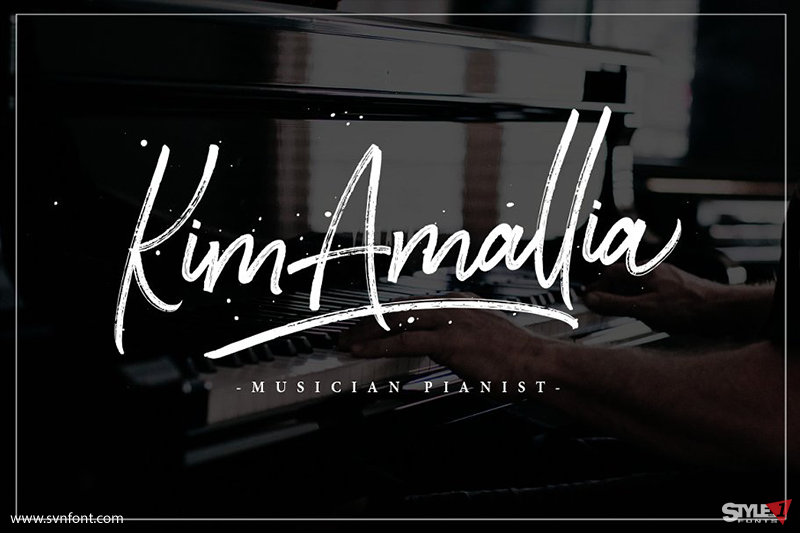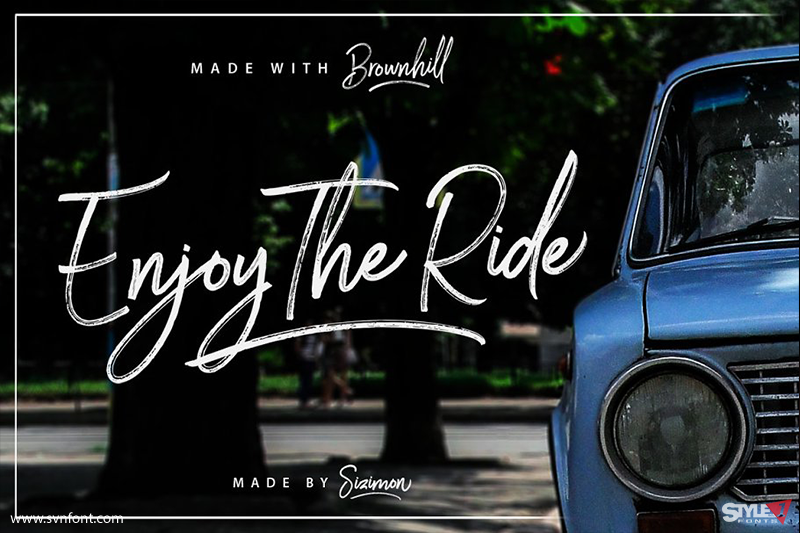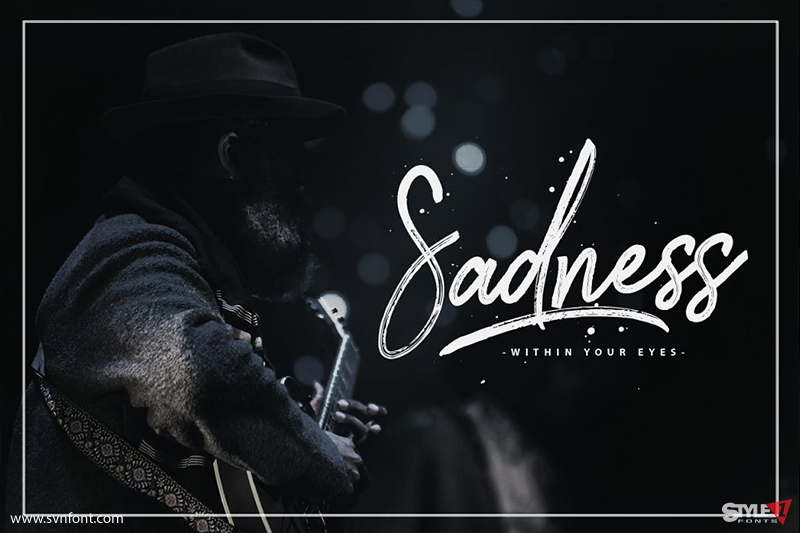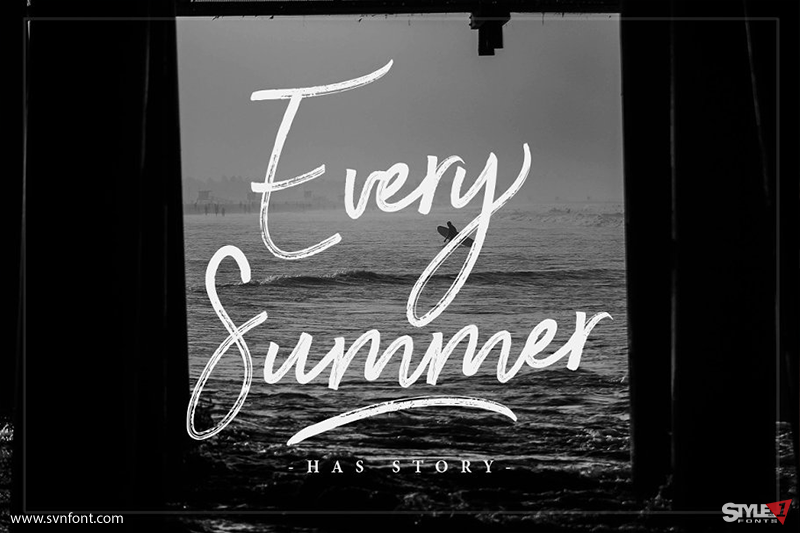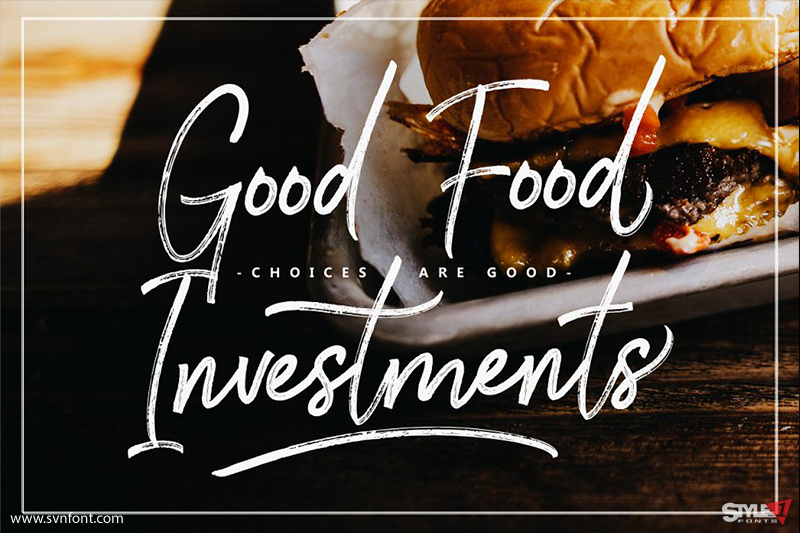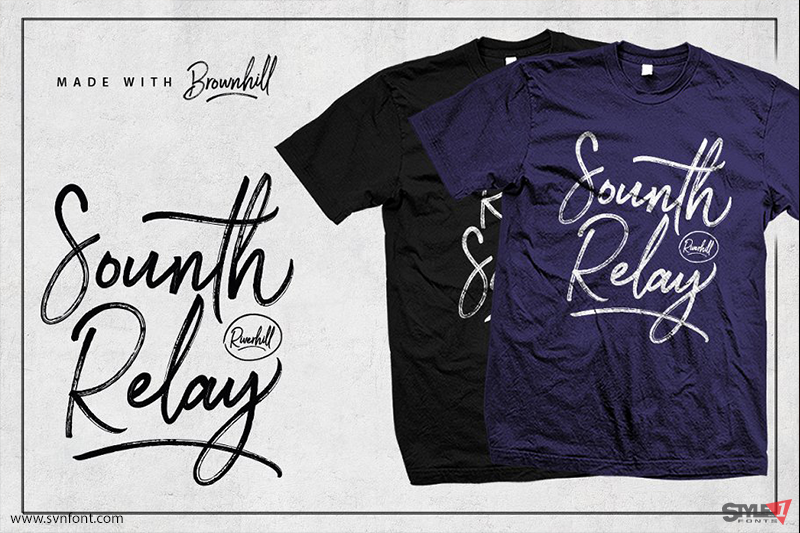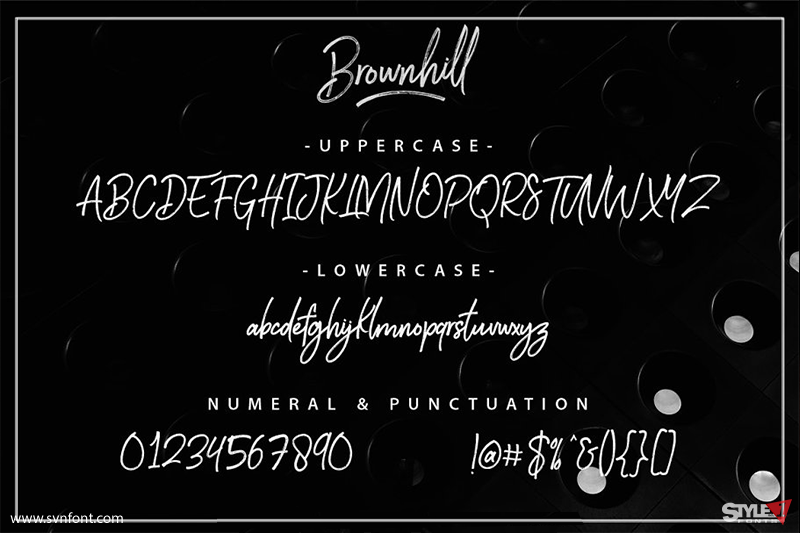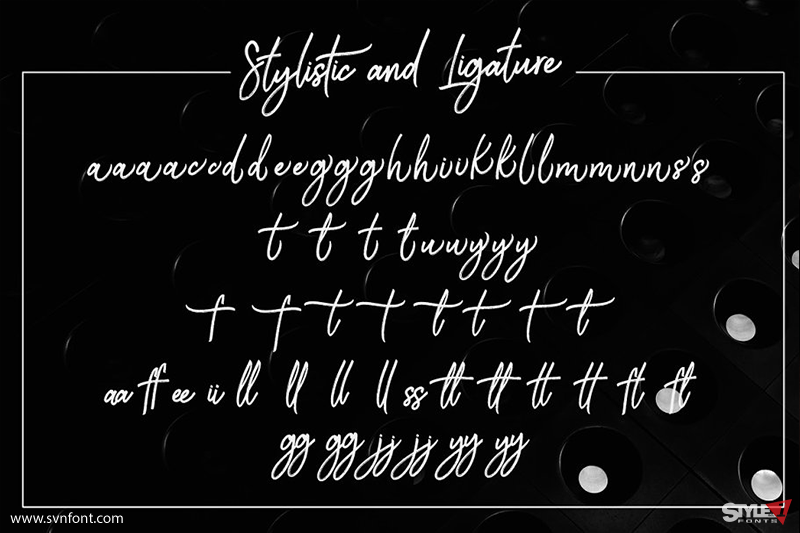
Brownhill Script là một bộ font chữ viết tay rất linh hoạt. Font đặc biệt phù hợp cho logo, thẻ tên, câu trích dẫn viết tay, bao bì sản phẩm, hàng hóa, mạng xã hội và thiệp chúc mừng. Đồng thời, font giúp việc thiết kế áo thun và các sản phẩm khác trở nên nhanh chóng, tiết kiệm thời gian. Brownhill Script bao gồm đầy đủ chữ hoa, chữ thường, hệ thống dấu câu phong phú, chữ số và hỗ trợ đa ngôn ngữ.
Nhà thiết kế: sizimon